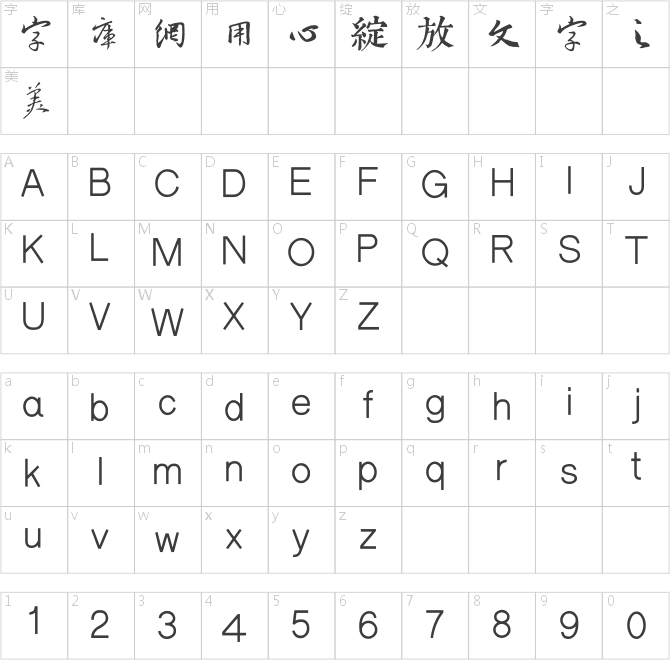
字体名称: 邯郸王羲之千字
邯郸王羲之千字文
王羲之(303—361,一说321—379),字逸少,东晋时期书法家,有“书圣”之称。琅琊临沂(今山东临沂)人,南渡后居会稽山阴(今浙江绍兴),晚年隐居剡县金庭。 历任秘书郞、宁远将军、江州刺史,后为会稽内史,领右将军。其书法兼善隶、草、楷、行各体,精研体势,心摹手追,广采众长,备精诸体,冶于一炉,摆脱了汉魏笔风,自成一家,影响深远。风格平和自然,笔势委婉含蓄,遒美健秀。李志敏评价:“王羲之的书法既表现以老庄哲学为基础的简淡玄远,又表现以儒家的中庸之道为基础的冲和。”代表作《兰亭序》被誉为“天下第一行书”。在书法史上,他与其子王献之合称为“二王”。
邯郸王羲之千字文字体字库是一款让人赏心悦目、百看不厌的中文字体,适合各类广告和产品包装设计应用,字体大小6.52MB,格式为ttf字体,上传用户是邯郸字库,作者/版权方为韩绍杰